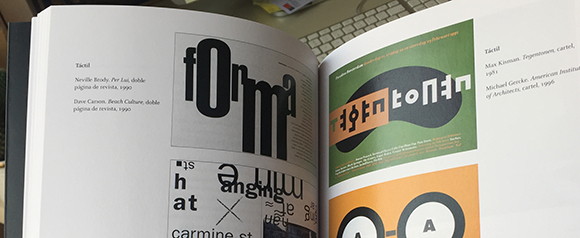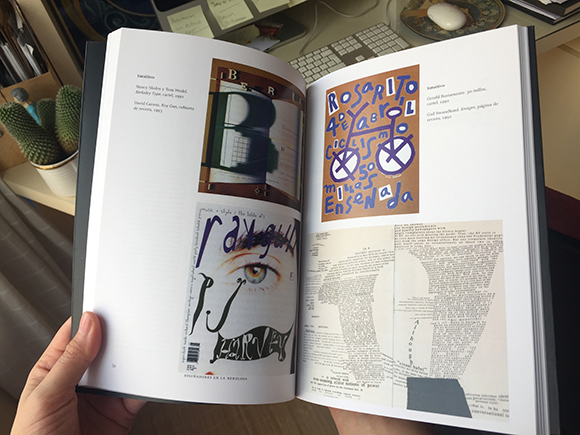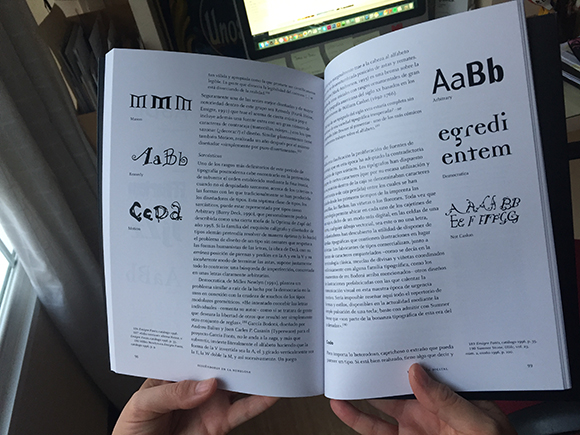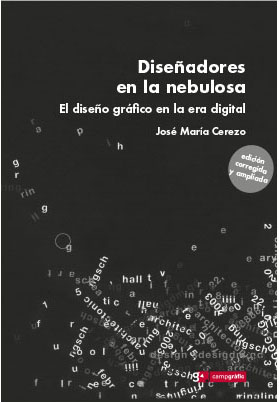
Corría el año 1997, y un servidor asistía a un master de diseño editorial impartido en el IED (Istituto Europeo di Design). Por aquel entonces el mundo del diseño gráfico se encontraba revuelto por la convulsión que supuso la aparición de la autoedición unos diez años atrás y el cambio que esta tecnología supuso sobre todo en el ámbito de la tipografía.
La tipografía digital había derribado la última barrera que se interponía entre el diseñador y el acceso total a las tipografías que utilizaban. Se dio en llamar a este periodo como la “democratización de la tipografía” y fue muy interesante porque abrió una vías expresivas novedosas sobre todo a la hora de utilizar las letras:
Recuerdo también con agrado que por aquella época, a través de la ventana que Internet abrió al mundo, nos poníamos en contacto con las primeras fundiciones digitales independientes y estas te enviaban con entusiasmo un paquete lleno de folletos publicitarios de todo tipo: ¡¡el que me envió Emigre no cabía en el buzón!! Y si alguno de nosotros conseguía una tipografía de rabiosa actualidad la exhibía como un auténtico trofeo. Así estaban las cosas cuando, volviendo ya a mis clases, un día los coordinadores nos avisaron de que a la semana siguiente empezábamos las clases de tipografía. Allí me encontré por primera vez con José María Cerezo. Podéis comprender como esa olla a presión tipográfica que yo tenía en la cabeza, de pronto quedó como alejada del fuego al caer en la red de sabios consejos, perspectiva histórica, conocimiento de la profesión de tipógrafo y compromiso con la cultura que Cerezo mostraba en sus clases.
No tengo que decir que cuando José María nos comentó que había publicado un libro sobre diseño y tipografía, me tiré de cabeza a comprarlo… si, se trataba de Diseñadores en la nebulosa. El diseño gráfico en la era digital.
Diseñadores en la nebulosa proporcionó a todos los interesados un marco de reflexión muy necesario sobre diseño y tecnología además de abrir la puerta a racionalizar de alguna manera la avalancha de tipografías digitales que se nos vino encima, en una época en la que estábamos prácticamente a oscuras sobre la revolución que estaba ocurriendo en el mundo del diseño y las artes gráficas: Así no fue nada raro que al poco tiempo de su aparición ya era considerado todo un clásico.
Lo primero que me gustaría destacar de este libro es la plena vigencia de la reflexión que el autor nos ofrece sobre el diseño, los diseñadores y el contexto tecnológico. Una reflexión necesaria en los años noventa con la revolución provocada por el ordenador personal y el entorno digital y pertinente en los inicios del siglo XXI ya que la idea de cambio, evolución y como el diseñador se enfrenta al mismo forma parte de nuestro propio ámbito profesional.
¿Qué significó la aparición del ordenador y como afectó a los procesos prácticos y mentales del diseñador? ¿Se trataba de una herramienta más? ¿Cómo afectó al estilo? Unas preguntas a las que Cerezo responde desde la reflexión y desde la práctica del oficio a lo largo de tres apartados en los que divide la obra: el primero de ellos que se centra en la aparición del ordenador y sus consecuencias: la carga de nuevas responsabilidades para los diseñadores a cambio de una mayor libertad creativa, como afectan los nuevos procesos productivos a la profesión y la constatación de que sobre la tecnología se encuentran las ideas; el segundo que se ocupa del estilo que la nueva herramienta proporciona y en el que el autor repasa algunas de las categorías habituales a la hora de catalogar un estilo para acabar proponiendo un mapa del nuevo estilo digital y el tercero que se centra en la tipografía y los nuevos caminos que se la presentan en este nuevo entorno.
En conjunto funcionan como un auténtico “estado del arte” que refleja de forma poderosa y certera tanto las incertidumbres como las posibilidades que surgieron en aquella época en torno al diseño como expresión cultural y sector económico.Esta nueva edición, además, presenta novedades interesantes ya que ha sido revisado completamente por el autor, se han añadido imágenes a todo color, cuenta con una introducción de la historiadora y teórica del diseño Anna Calvera, tristemente fallecida hace unos días, y está prologado por el escritor y articulista José Antonio Millán.
A nosotros no nos queda más que añadir que felicitar a la editorial Campgràfic por la iniciativa de volver a editar este libro que posibilita que una de las voces más autorizadas e interesantes del ámbito del diseño y la tipografía de nuestro país vuelva a estar presente en los anaqueles de las librerías., a disposición de diseñadores, estudiantes e historiadores.
Diseñadores en la nebulosa. El diseño gráfico en la era digital
José María Cerezo